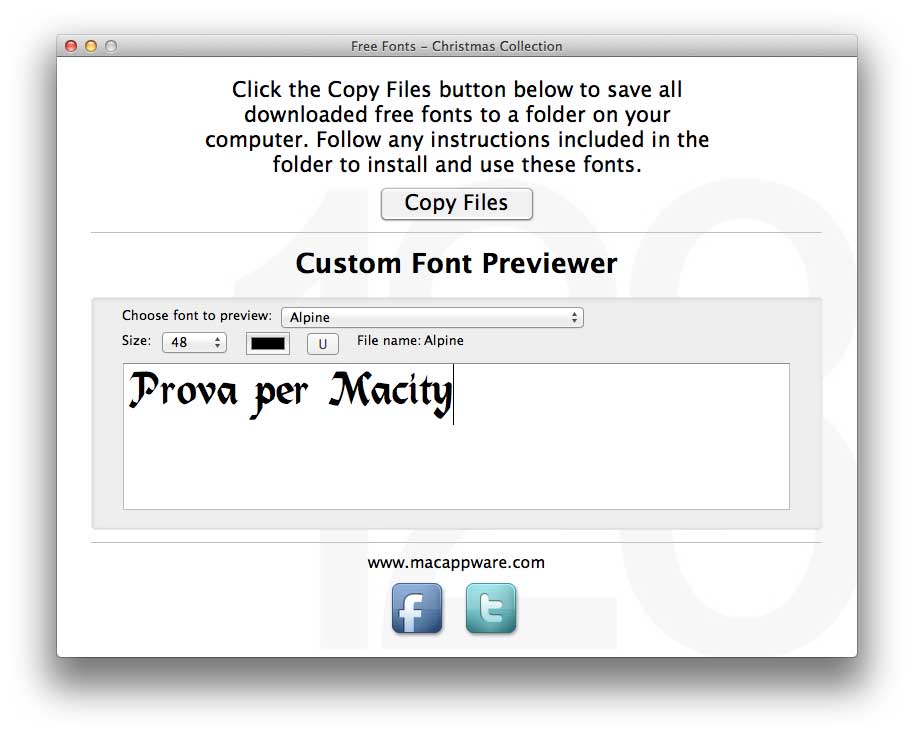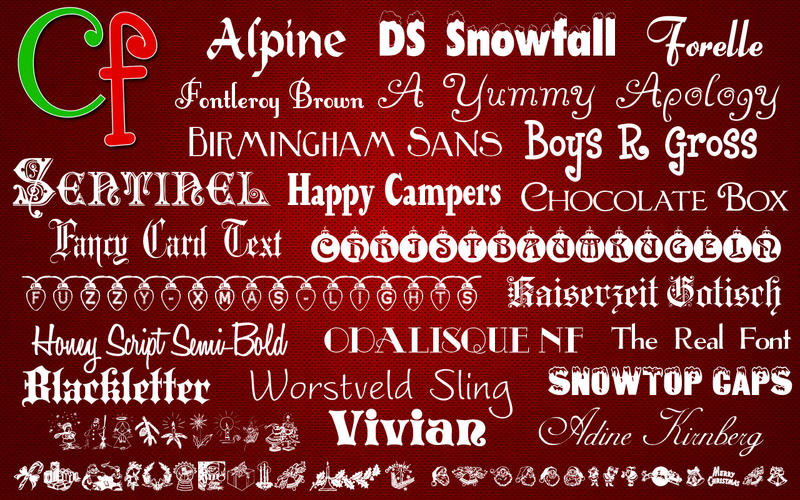
Christmas Collection: la raccolta font di Natale gratis su Mac App Store
Christmas Collection è una raccolta gratuita di 25 font a tema natalizio creati da designer professionisti, disponibili con vari stili, ottimi per le prossime festività. Grazie a questo pacchetto possiamo aggiungere al nostro Mac stili e caratteri perfetti per creare calendari, biglietti di auguri, sfondi scrivania, brochure, inviti a feste, siti web e molto altro ancora.